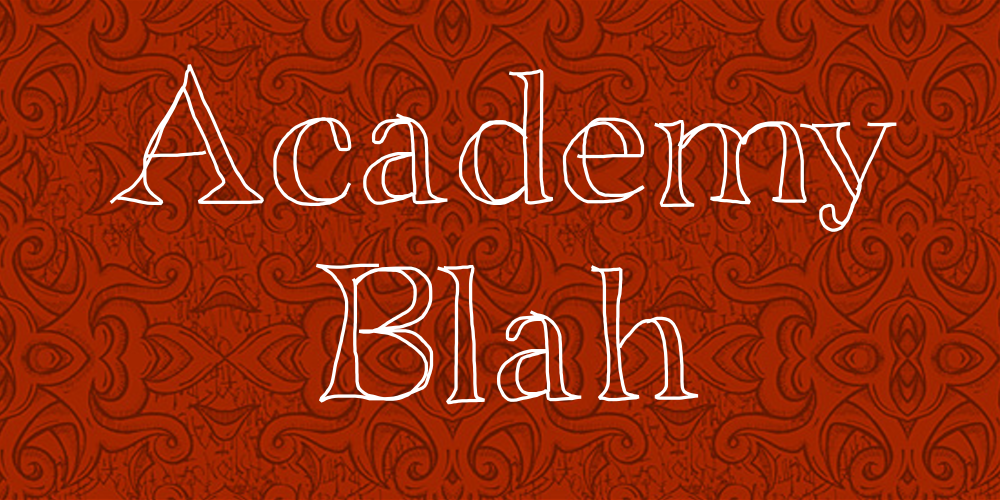
A Academia Blah Font é uma elegante fonte Serif que oferece profundidade e sofisticação para projetos digitais. Desenvolvida pelo designer Hamilton, essa fonte traz um ar de elegância às suas criações, especialmente adequada para trabalhos formais ou corporativos. Sua aparência sofisticada e detalhada destaca-se em texturas variadas e tipografia cuidadosamente criadas, proporcionando aos designers uma ferramenta versátil para expressar seu trabalho com precisão e estilo. Com um design que não só transmite confiabilidade e autoridade, mas também oferece um toque refinado aos projetos digitais, a Academia Blah Font é perfeita para aqueles buscando uma fonte Serif elegante para seus trabalhos mais importantes. Visite o website do designer para explorar mais detalhes sobre este talentoso projeto gráfico.